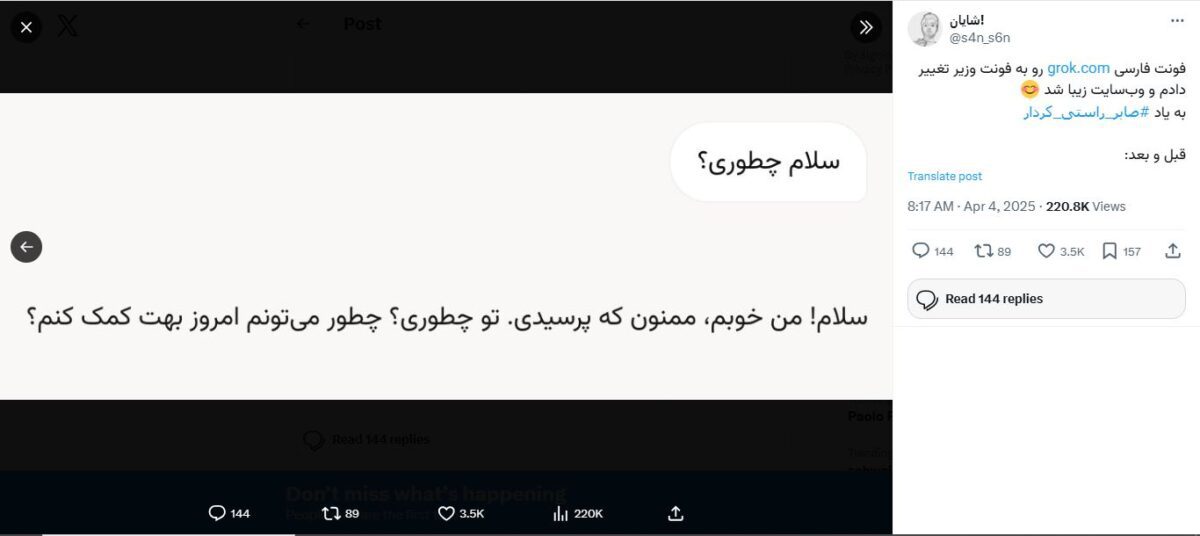
فونت وزیر متن به ایکس اضافه شد
فونت وزیرمتن به ایکس اضافه شد
فونت فارسی «وزیرمتن» (Vazirmatn) به‌ تازگی به گزینه‌های نوشتاری کاربران شبکه‌ اجتماعی ایکس (توییتر سابق) اضافه شده است.
به گزارش تک‌ناک، این خبر نخستین‌بار در پستی منتشرشده توسط یکی از مهندسان ایرانی شاغل در تیم فنی ایکس اعلام شد. وی اضافه شدن وزیرمتن را گامی مهم در جهت بهبود خوانایی و نظم بصری متن برای کاربران فارسی‌زبان دانست و تأکید کرد که متن‌های منتشرشده با این فونت، نظم و زیبایی بیشتری خواهند داشت.
فونت وزیرمتن در اصل پروژه‌ای متن‌باز است، که از سال ۲۰۱۵ با هدف تأمین یک قلم ساده، خوانا و مناسب برای صفحات وب و رابط کاربری آغاز شده بود.
این فونت از زیرمجموعه‌ طراحی‌های «نئو‌گروتسک» است و هم برای متون فارسی/عربی و هم برای متون لاتین گسترش یافته ‌است. بسیاری از وب‌سایت‌های ایرانی نیز پیش از این به‌ دلیل سادگی خطوط، خوانایی مناسب در سایزهای گوناگون و هماهنگی مناسب با رابط‌های وب و نرم‌افزاری از وزیرمتن استفاده می‌کردند.
اضافه شدن فونت وزیرمتن به ایکس
فونت وزیرمتن در ایکس
طراح اصلی وزیرمتن، صابر راستی‌کردار، مهندس و طراح فونت بود. این اثر فنی و هنری او در جامعه نرم‌افزار آزاد و متن‌باز از جایگاه قابل‌ توجهی برخوردار است.
متأسفانه راستی‌کردار در ۲۳ آبان ۱۴۰۲ در سن ۳۶ سالگی بر اثر ابتلا به سرطان ریه و لگن درگذشت. ارج‌گزاری به تلاش‌های او در این اقدام فنی در سطح یک پلتفرم جهانی به چشم می‌خورد.
اضافه شدن وزیرمتن به رابط کاربری ایکس می‌تواند چند تأثیر مهم داشته باشد: نخست، خوانایی بهتر نوشته‌ها و کامنت‌ها برای کاربران فارسی‌زبان؛ دوم، کاهش مشکلاتی مانند بهم‌ریختگی یا ناهماهنگی حروف و فونت در دستگاه‌ها و مرورگرهای مختلف و سوم، ارتقای هویت بصری فارسی در فضای تعاملی و عمومی، که می‌تواند حس مشارکت و اتصال فرهنگی کاربران را تقویت کند.